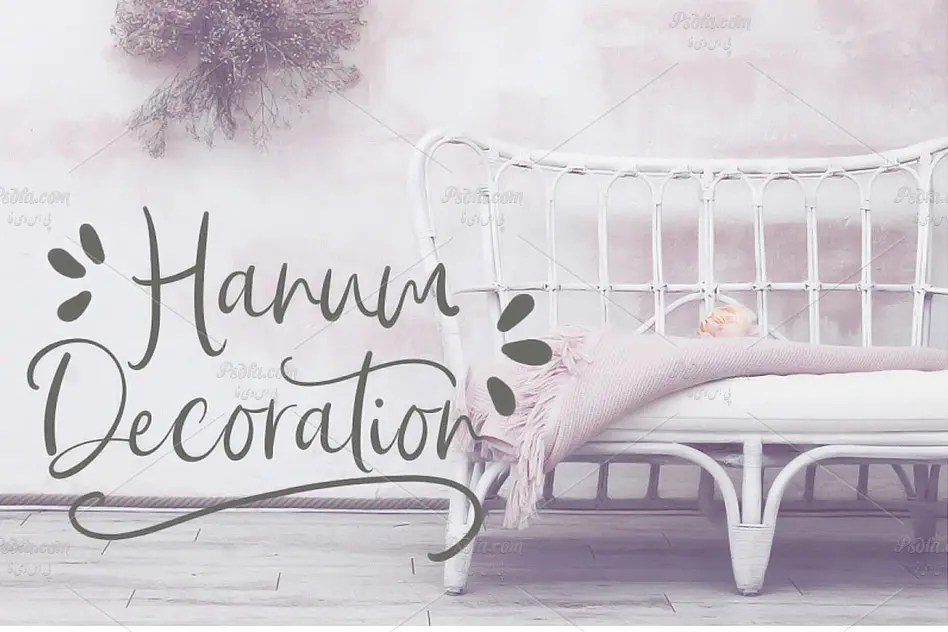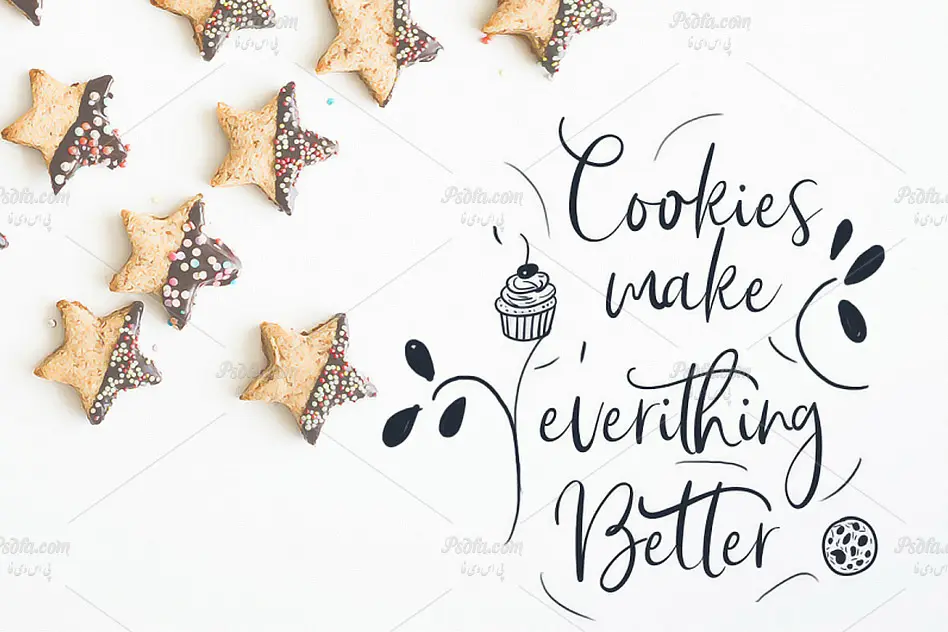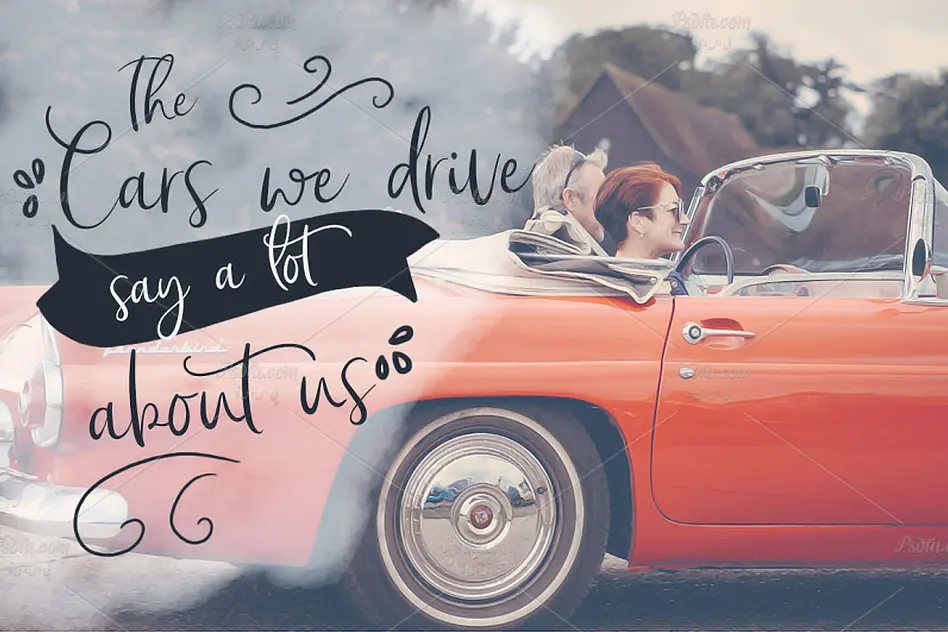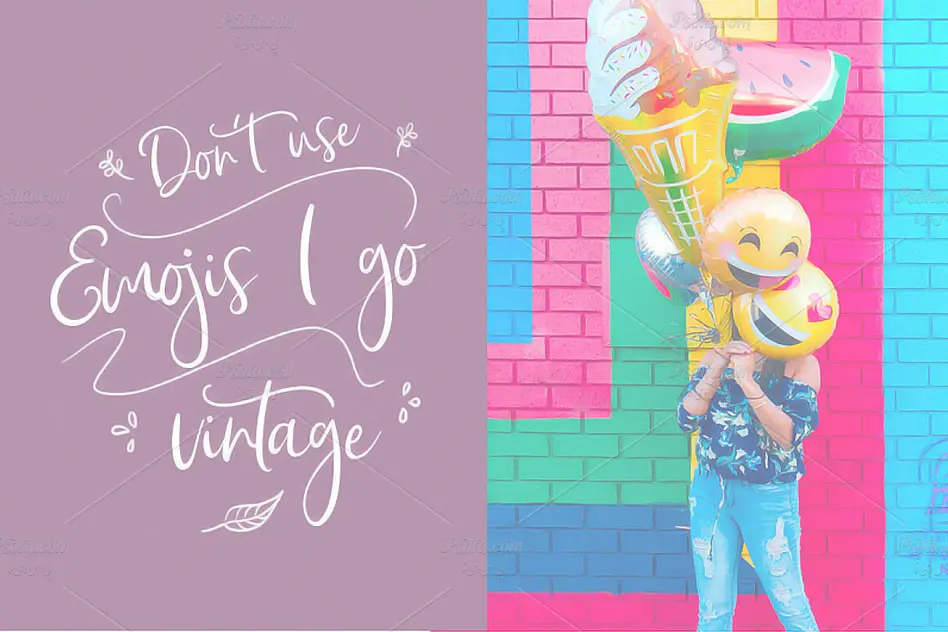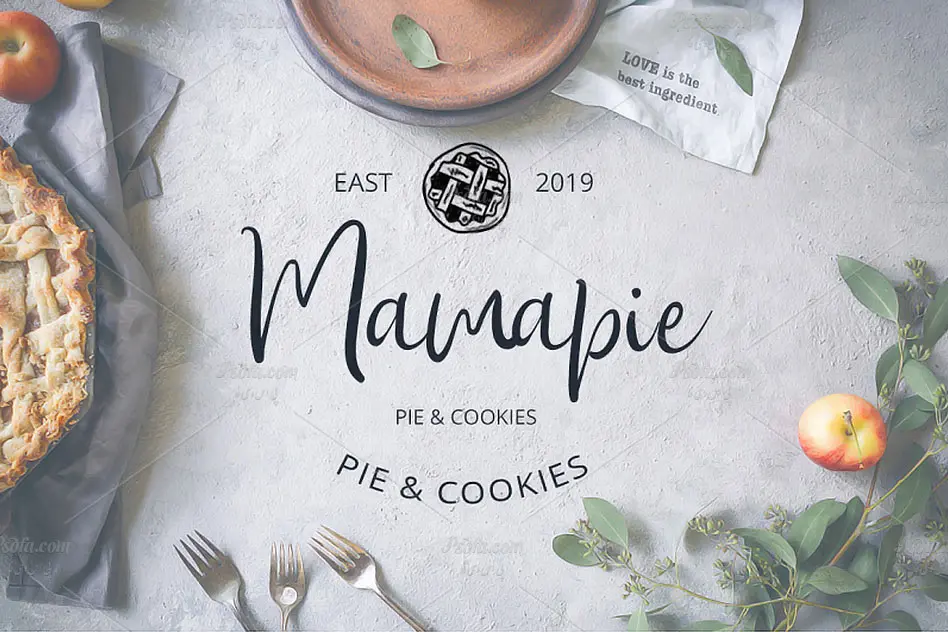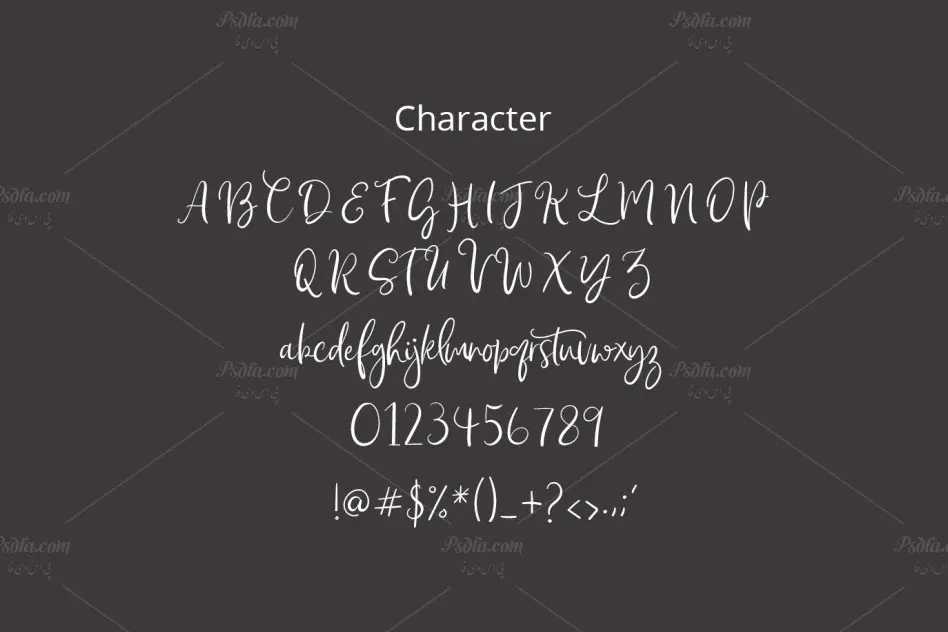
در این مطلب شاهد فونت انگلیسی دستنویس شاهزاده راپانزل Princes Rapunzel مناسب جهت استفاده در طرح های گرافیکی می باشید. این فونت زیبا در قالب دو فایل ttf و otf بر روی سایت قرار گرفته است که با نصب یکی از این دو فرمت در پوشه فونت های سیستم خود قادر به استفاده از آن در تمام نرم افزارهای گرافیکی و ویرایشگر متن از جمله نرم افزار فتوشاپ ، ایلاستریتور ، افترافکت ، مجموعه نرم افزار آفیس و … خواهید بود. فونت Princes Rapunzel در وزن معمولی (Regular) طراحی شده است که از آن می توان در طراحی انواع کارت تبریک ، کارت پستال ، کارت عروسی ، پوستر ، بنر ، کارت ویزیت ، طراحی بر روی تی شرت ، چاپ بر روی ماگ و … استفاده نمود.
- نام فونت : Rapunzel